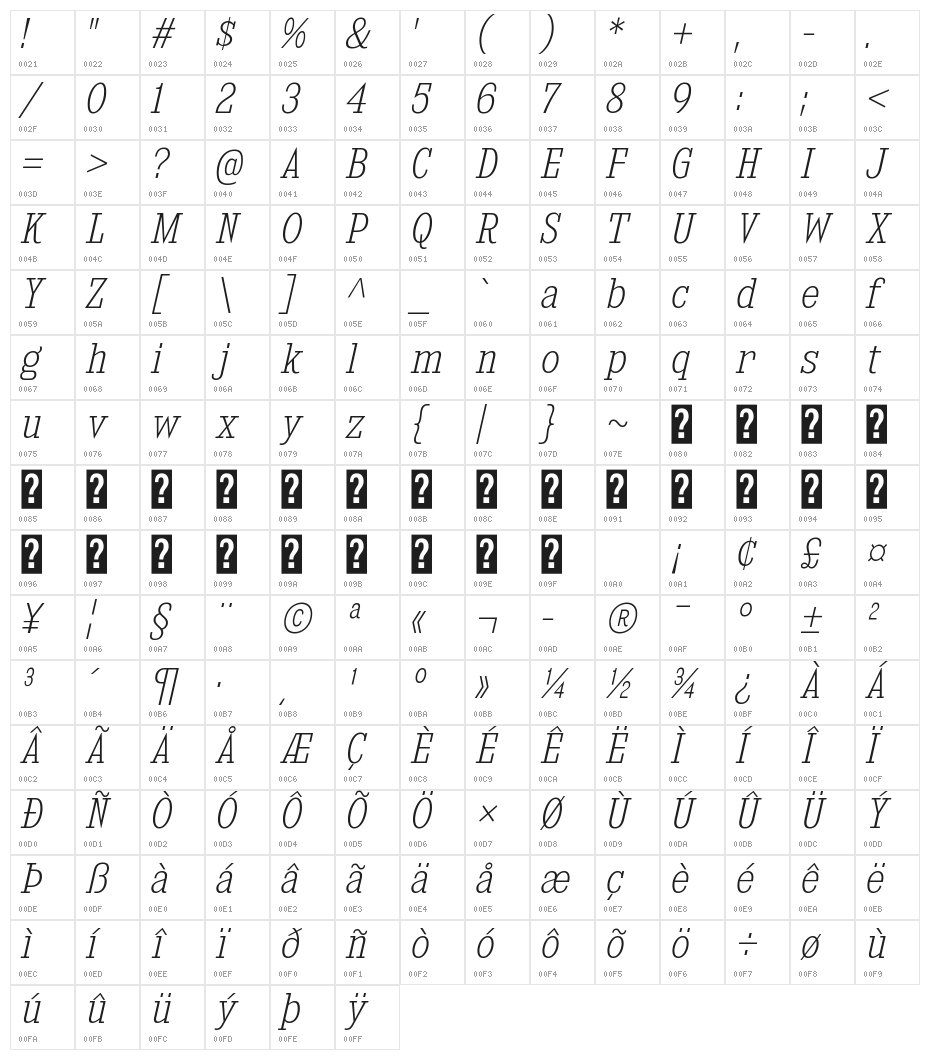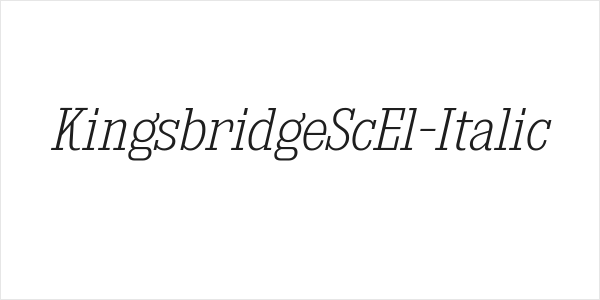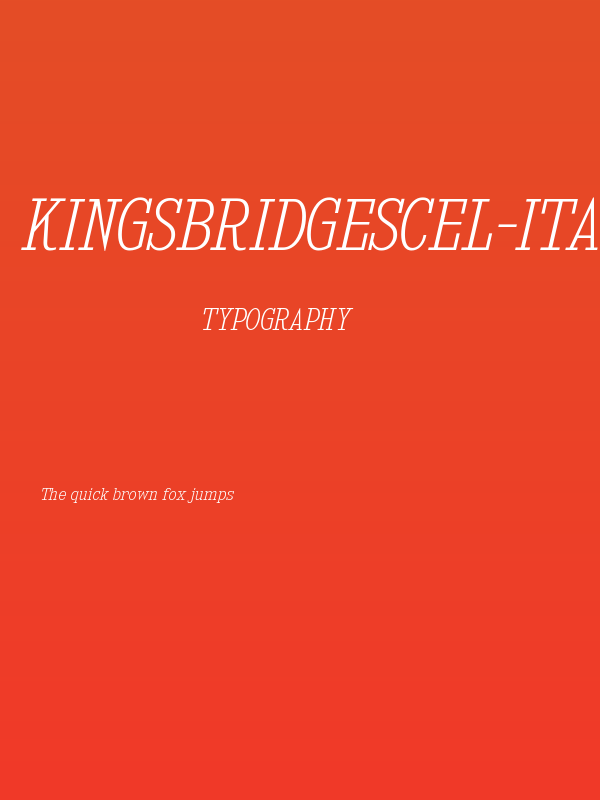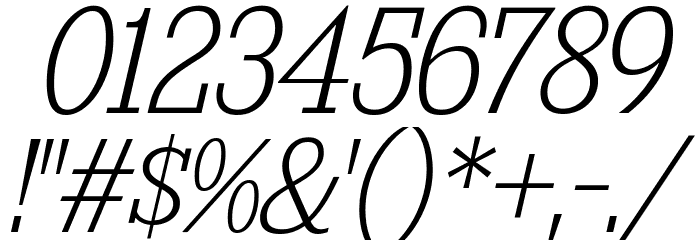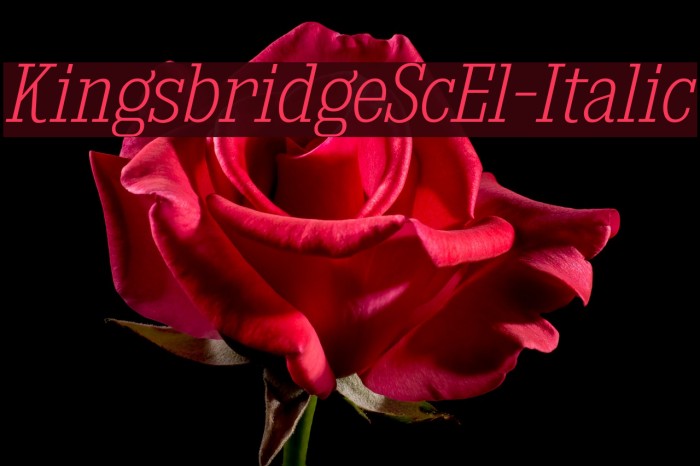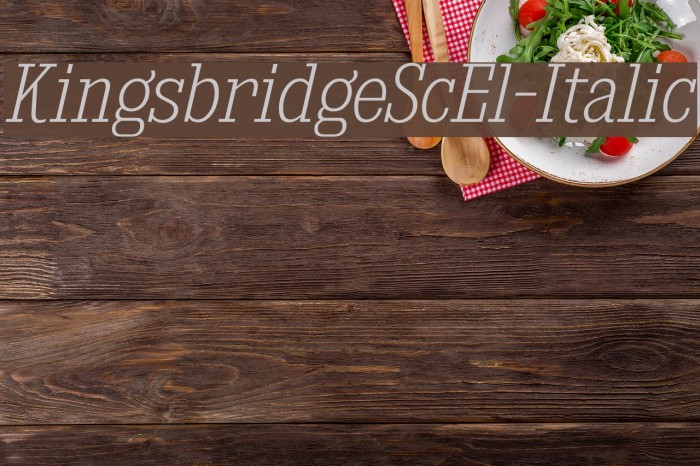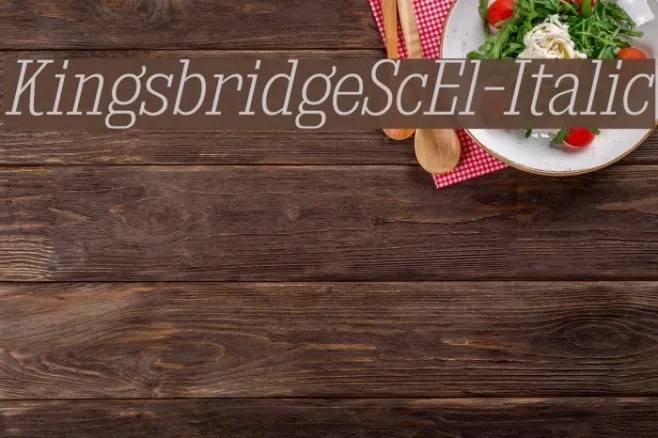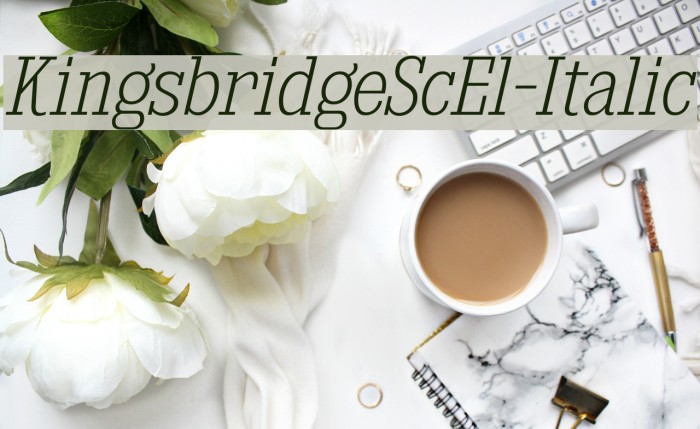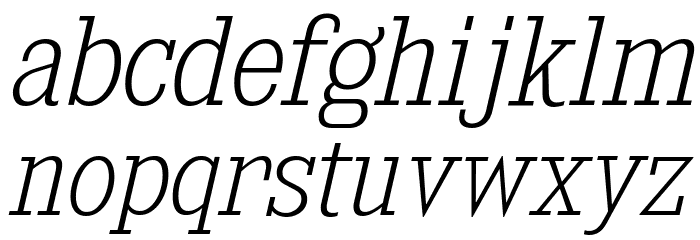
KingsbridgeScEl-Italic Font
| Familia de fuentes | Kingsbridge Sc El |
| Categorías | Serif |
| Estilo general | Modern Classic |
| Caso de uso | Headlines, Body text, Logos |
| Proyectos propuestos | Ideal for editorial design, book covers, formal invitations, and branding materials that require a touch of elegance and sophistication. |